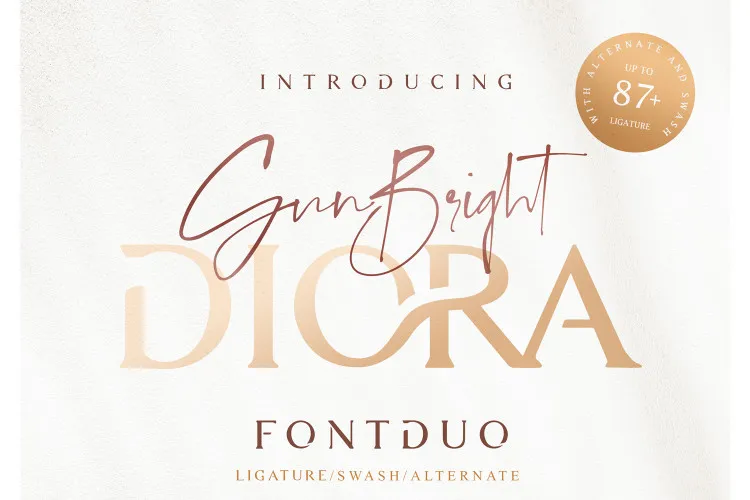
Diora Sunbright Font Duo – Fonte Grátis
Diora Sunbright Font Duo
Descubra a Diora Sunbright Script & Serif Font Duo, uma elegante dupla de fontes com estilo serífero e escrita manuscrita. Esta combinação única é perfeita para designers buscando dar um toque luxuoso e inovador em suas criações. Através da Ratin Creative, a Diora Sunbright Font Duo oferece uma dupla de fontes que inclui uma assinatura escrita à mão com estilo serífero natural. Especificamente projetada para o mercado das marcas femininas e casamentos, esta combinação pode dar um toque exclusivo a qualquer projeto de marca pessoal ou cartão de convite de casamento. Além disso, ela é ideal para uma variedade de aplicações, desde marcas pessoais até embalagens publicitárias, tudo isso com o charme único e sofisticado da Diora Sunbright Font Duo.